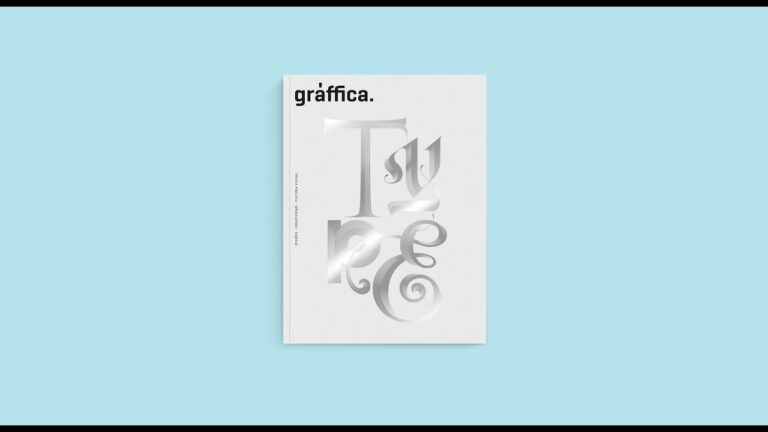
Claves para una Tipografía Efectiva en el Diseño de Revistas Especializadas
La tipografía es una de las herramientas más importantes en el diseño de revistas especializadas, ya que puede marcar la diferencia entre una publicación impactante y una que pase desapercibida. En este artículo, exploraremos la importancia de elegir la tipografía adecuada para captar la atención del lector y transmitir el mensaje de forma clara y efectiva. Acompáñanos en este viaje por el fascinante mundo de la tipografía en el diseño editorial.
• La tipografía en el diseño de revistas especializadas juega un papel crucial en la legibilidad y la estética del contenido.
• Es importante seleccionar cuidadosamente la tipografía para reflejar la identidad de la revista y el público objetivo.
• El uso de diferentes tipos de fuentes, tamaños y estilos puede ayudar a jerarquizar la información y guiar la lectura.
• La coherencia en la tipografía a lo largo de la revista contribuye a una experiencia de lectura más uniforme y agradable.
• Experimentar con combinaciones de tipografías puede dar un toque único y creativo al diseño de la revista.
¿Qué tipo de letra se usa en las revistas?
Las revistas suelen utilizar tipografías de las familias Serif y Sans Serif para garantizar una alta legibilidad. Estos tipos de letra son elegidos por su claridad y facilidad de lectura, lo que permite a los lectores disfrutar del contenido sin dificultad. La legibilidad es un factor crucial en el diseño de revistas, y las tipografías Serif y Sans Serif cumplen con esta necesidad de manera efectiva.
La elección de tipografías para revistas se basa en la legibilidad, y es por eso que las familias Serif y Sans Serif son las más comunes. Estos tipos de letra ofrecen una excelente claridad en la impresión, lo que es fundamental para la presentación de textos extensos en las páginas de una revista. Al priorizar la legibilidad, las revistas garantizan una experiencia de lectura cómoda y atractiva para sus audiencias.
La legibilidad es un aspecto fundamental en el diseño de revistas, y las tipografías Serif y Sans Serif son seleccionadas por su capacidad para ofrecer una lectura clara y fácil. Estos tipos de letra permiten que el contenido de las revistas sea accesible y atractivo para los lectores, lo que contribuye a la calidad general de la publicación. Al utilizar estas familias tipográficas, las revistas pueden asegurarse de que su contenido sea disfrutado por una amplia audiencia.
¿Cuál es el tipo de fuente de información de una revista?
Revistas: Son publicaciones periódicas que ofrecen información actualizada y son fundamentales para mantenerse al día en diversos temas.
¿Qué es la tipografía en el diseño editorial?
La tipografía es una herramienta esencial en el diseño editorial, ya que se encarga de transmitir mensajes de manera efectiva a través de la apariencia y el estilo de las palabras. En proyectos de diseño, la tipografía juega un papel crucial al formar parte de un conjunto visual que garantiza la adecuada transmisión de información.
Dominando la tipografía para destacar en diseño editorial
En el mundo del diseño editorial, la tipografía juega un papel fundamental para captar la atención del lector y transmitir el mensaje de manera efectiva. Dominar el uso de fuentes, tamaños y estilos es clave para crear diseños atractivos y funcionales. La elección adecuada de tipografía puede hacer que un diseño destaque y sea memorable, por lo que es importante dedicar tiempo a seleccionar la opción más adecuada para cada proyecto.
Además de la elección de tipografía, es importante tener en cuenta la jerarquía visual y la legibilidad en el diseño editorial. El uso de diferentes tamaños, pesos y estilos de fuente puede ayudar a guiar al lector a través del contenido y resaltar la información más relevante. Al combinar una tipografía cuidadosamente seleccionada con una disposición equilibrada y una paleta de colores adecuada, se puede lograr un diseño editorial impactante y efectivo que destaque entre la multitud.
Secretos de la tipografía para revistas de alto impacto
La tipografía es un elemento crucial en el diseño de revistas de alto impacto. La elección de fuentes adecuadas puede marcar la diferencia entre una publicación atractiva y una aburrida. Es importante seleccionar fuentes legibles, pero también con personalidad y estilo que se ajusten al tono de la revista.
Además de la elección de fuentes, es fundamental prestar atención al espaciado y la alineación del texto. Un espaciado adecuado entre letras y líneas puede mejorar la legibilidad y la estética del diseño. Del mismo modo, la alineación del texto debe ser coherente y cuidadosa para garantizar una apariencia profesional.
Otro aspecto a considerar es la jerarquía tipográfica. Utilizar diferentes tamaños, pesos y estilos de letra para destacar títulos, subtitulares y cuerpo de texto puede ayudar a guiar al lector a través de la revista de manera efectiva. En resumen, dominar los secretos de la tipografía es fundamental para crear revistas de alto impacto que cautiven a su audiencia.